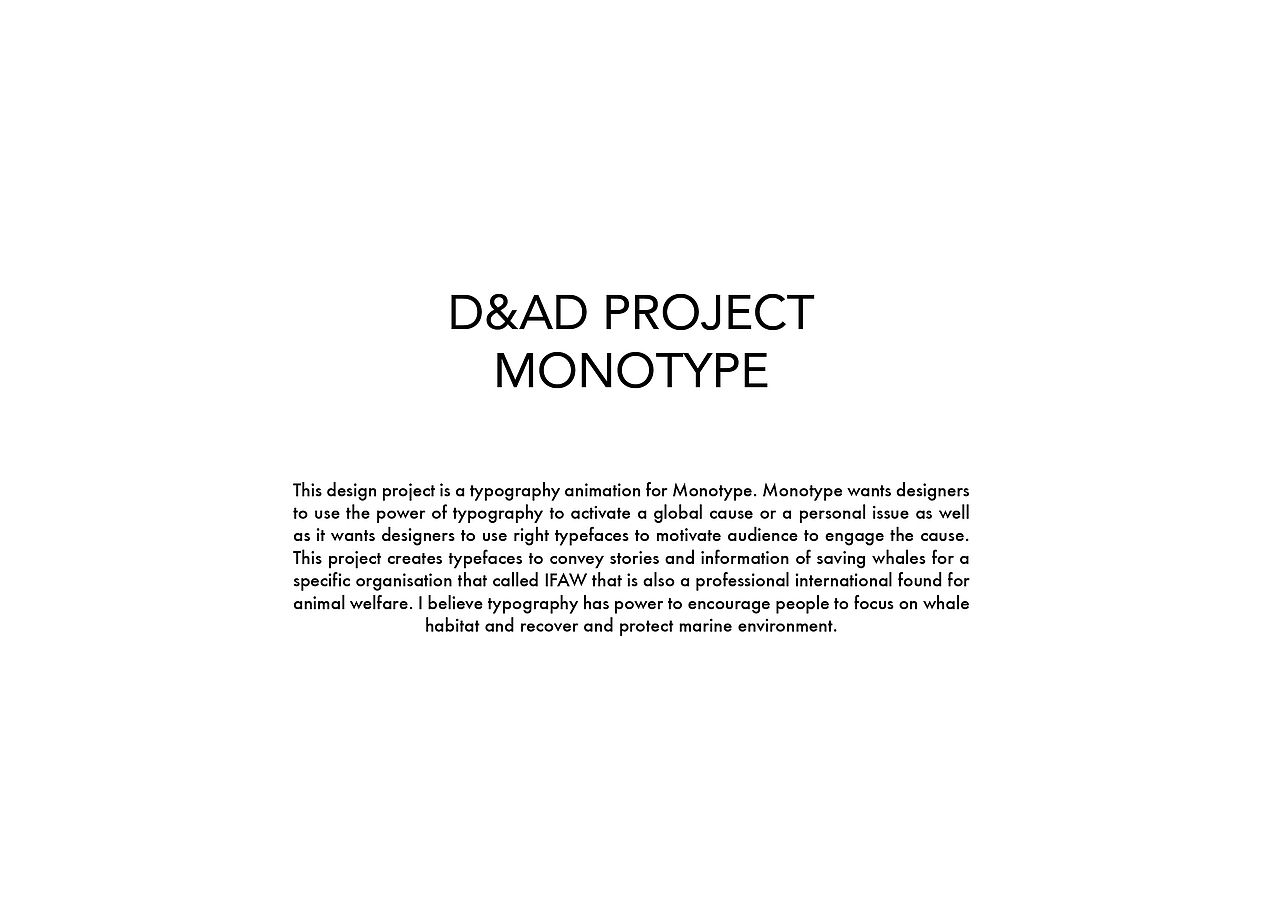
[公益字体广告][动画]Monotype-拯救鲸鱼
这个项目是为Monotype公司宣传字体而制作的字体动画。
Monotype公司希望设计者能够使用文字的力量去表达一个全球性的话题,
同时也希望设计者能够使用正确的字体去鼓励人们参与到这个话题或某个事件。
我制作的这个话题是希望通过流动的字体动画传达出拯救鲸鱼的信息。
我相信字体有它的力量去引导人们关注鲸鱼生态,去恢复和保护我们的海洋生态系统。
将字体的动画与鲸鱼死亡后的静态组合创作出鲸鱼公益广告。
动态的字体就像人们说出的话,快速的出现又快速的消失;
然而静态的死亡鲸鱼却永远静止在大自然中,在我们不知道的地方悄悄毁灭着。
采用这种形式去告诉人们鲸鱼也需要自己发声,它们也需要安全的环境去成长。